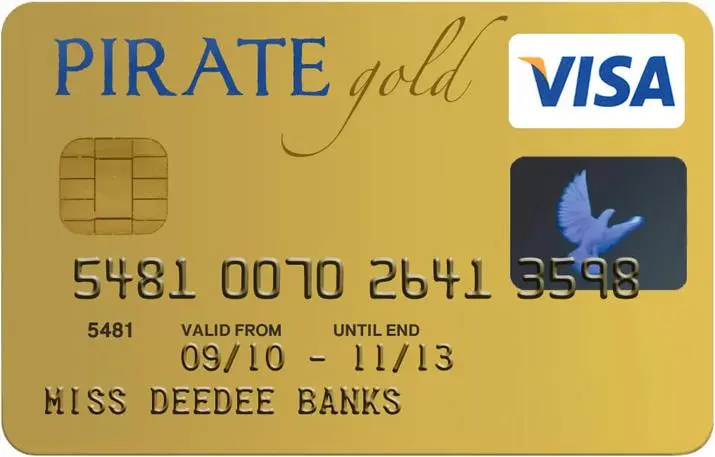
Esta font ‘Credit Card’ é uma elegante escolha para qualquer design que exige estilo sério e transparência. Com seu risco característico, ela traz a essência do tipo serif à sua página ou projeto, adaptando-se perfeitamente para nomes de empresas e marcas com um toque sofisticado. Cada linha da fonte foi cuidadosamente projetada pelo designer Hamilton, garantindo um equilíbrio entre modernidade e elegância que torna o texto legível mesmo em uma superfície aérea. Suas linhas finas e suas bordas arredondadas proporcionam um visual clean sem perder sua identidade personalizada. Ideal para créditos de cartão de crédito ou qualquer aplicação onde você deseja transmitir ao seu público que seu negócio está à altura da importância do pagamento, este é o recurso gráfico perfeito. Confortável e versátil, ‘Credit Card’ oferece a oportunidade de criar um design visual profissional e confiável.